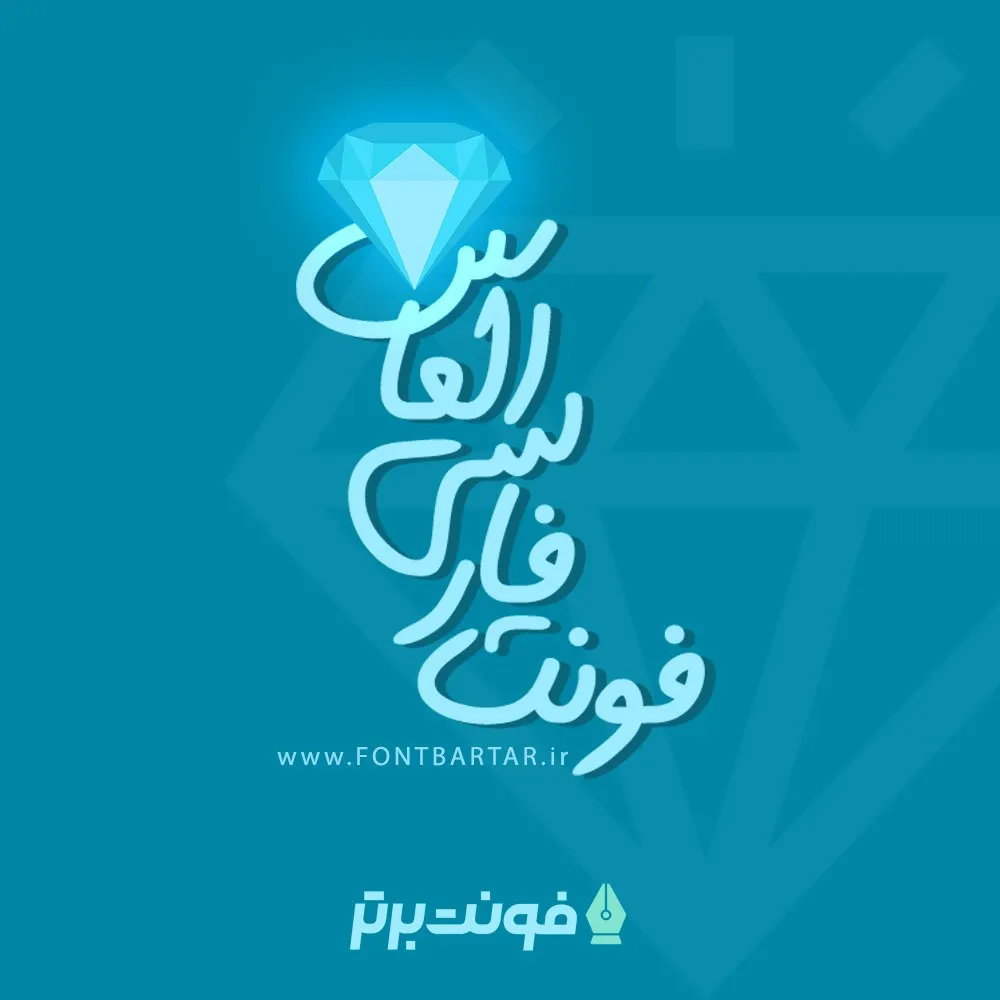
فونت دست نویس الماس
فونت دستنویس الماس
فونت دستنویس الماس یک فونت فارسی و دست نویس است که قدرت خودش را از روی دست خط سرکار خانم طیبه مرادی گرفته شده است .شخصیت و روحیه فونت الماس روان ، ساده ، عاشقانه و با طراوت است که می تواند براحتی در قالب آثار هنری جای گرفته و خود نمایی کند.
چرا فونت دست نویس الماس؟
• فونت دست نویس الماس با دقت و حساسیت خاصی طراحی شده تا شباهت زیادی با دستخط اصلی داشته باشد .
• حروف فونت دستنویس الماس روان، ساده و با طراوت که حس آرامش را به مخاطب منتقل میکنه.
• حروف و کلمات جایگزین برای خوانایی بهتر در فونت فارسی الماس قرار گرفته تا خوانایی فونت بیشتر شود.
• این فونت دارای کنتراست و ضخامت خوبی است که شباهت آن به یک متن دست نویس را بیشتر میکند.
• فونت فارسی الماس دارای کرنینگ متعادل و اعراب هوشمند برای هر حرف است.
• و از همه مهم تر فونت فارسی الماس،از زبان کردی و عربی پشتیبانی  می کند.
فونت الماس